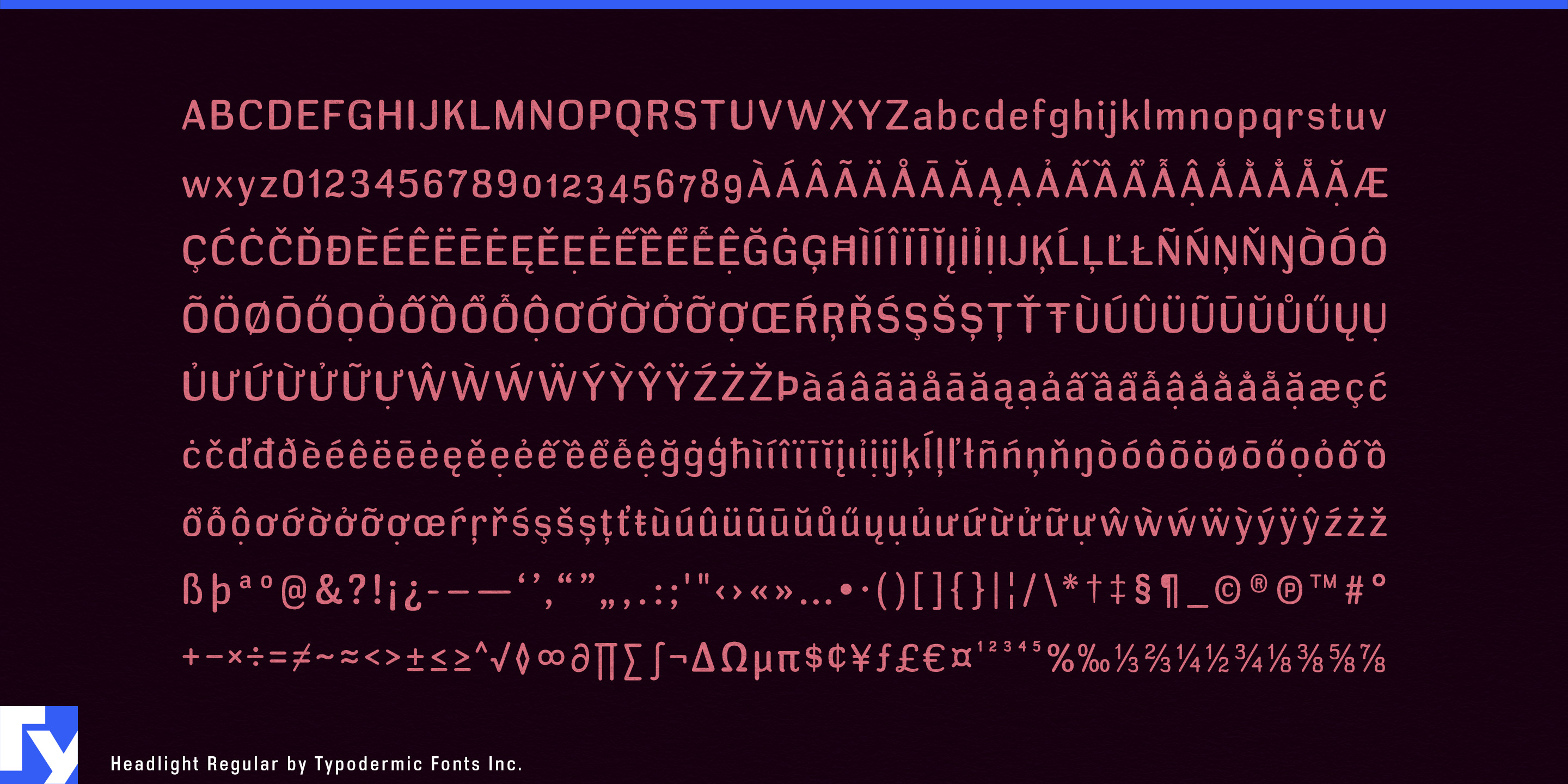
Headlight
Manche Maschinen müssen Menschen begegnen.
Ein Serviceroboter in einer Hotellobby, eine Paketstation vor einem Wohnhaus oder ein Check-in-Terminal am Flughafen darf nicht wie Fabrikausrüstung aussehen. Geht die Gestaltung jedoch zu weit in Richtung freundlicher runder Typografie, kann robuste Hardware spielzeughaft wirken. Headlight besetzt den nützlichen Raum zwischen diesen Extremen.
Ihre mechanisch rechtwinklig geprägten, superelliptischen Formen geben den Buchstaben eine technische Grundlage. Weiche Endungen und humanistische Strichstärkenmodulation nehmen der Geometrie zugleich ihre Strenge. Das Ergebnis wirkt industriell gefertigt, ohne militarisiert zu sein, und zugänglich, ohne niedlich zu werden.
Serviceroboter sind eine besonders naheliegende Anwendung. Lieferroboter in Hotels, Servierroboter in Restaurants, Reinigungsmaschinen, Verkaufsassistenten und Lieferflotten auf dem Campus brauchen Namen und Erscheinungsbilder, die ihre Funktion erkennen lassen, ohne bedrohlich zu wirken. Headlight kann Roboternamen, Modellfamilien, Gehäuseaufkleber, Grafiken an Dockingstationen und Ausstellungsdisplays übernehmen, während eine schlichtere Begleitschrift Diagnosedaten und umfangreiche Informationen der Benutzeroberfläche vermittelt.
Selbstbedienungsgeräte stellen weitgehend dieselbe Aufgabe. Paketstationen, Hotel-Check-in-Terminals, Fahrkartenautomaten, intelligente Verkaufssysteme, automatische Abholschränke und Parkgebührenautomaten verbinden starre Industriegehäuse mit einem Ort menschlicher Interaktion. Headlight gibt Produktnamen, Dienstnamen, Gehäusegrafiken und Anleitungsüberschriften einen technischen Charakter, der höflich und zugänglich bleibt.
Öffentliche Ladesysteme und gemeinsam genutzte Mobilitätsangebote führen diese Rolle im Freien fort. Ladestationen für Elektroautos, Fahrrad- und Scooter-Docks, Batteriewechselstationen und Mobilitätsterminals sind Infrastruktur, die zugleich als Konsumprodukt funktioniert. Gebäudezugangssysteme wie smarte Gegensprechanlagen, Besucherterminals, Paketraum-Terminals und Aufzugs-Zielwahlsysteme stehen vor derselben Herausforderung: Sie müssen zur technischen Hardware gehören und sich zugleich angenehm in alltägliche öffentliche Räume einfügen.
Dieselbe Balance funktioniert bei der Hausautomatisierung, etwa bei Saugrobotern, automatischen Rasenpflegegeräten und smarten Haustiergeräten. Headlight ist eine runde technische Sans für Maschinen, mit denen Menschen tatsächlich umgehen müssen. Ihre rechtwinklige Prägung kennzeichnet die Technik, ihr weicher Aufbau erleichtert das Kennenlernen.